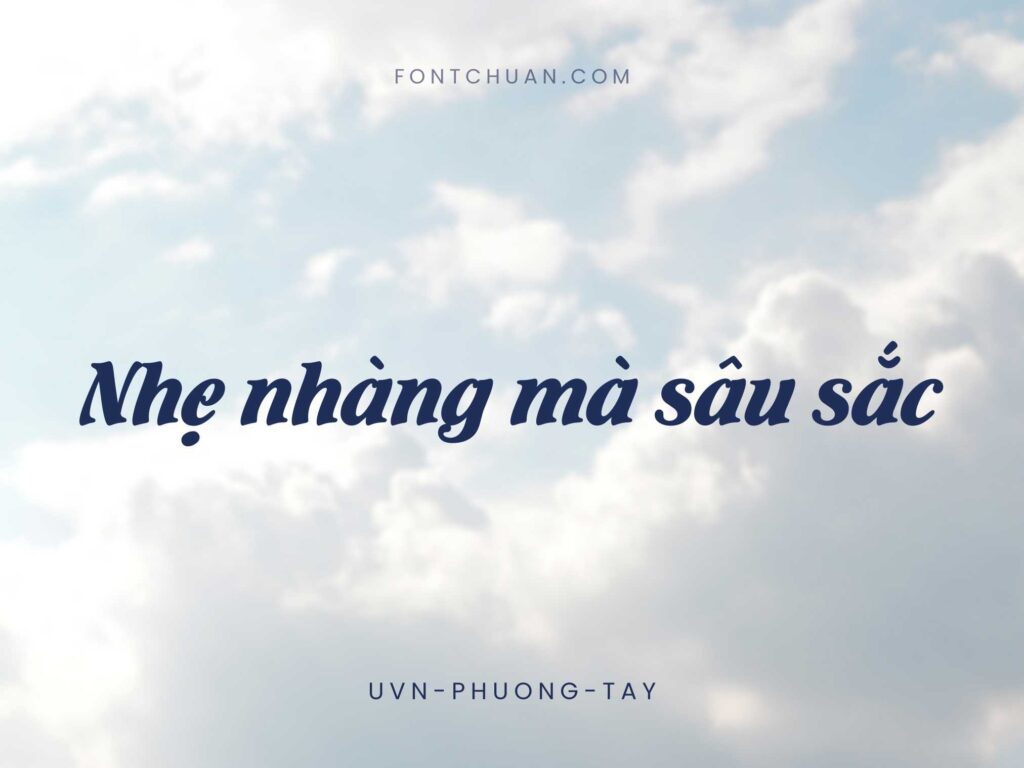
Font UVN Phuong Tay Việt Hóa
UVN Phương Tây là một phông chữ thư pháp mang phong cách nghệ thuật viết tay truyền thống. Được thiết kế với các nét bút lông mềm mại và uyển chuyển, phông chữ này tạo nên sự thanh thoát và tinh tế cho các tác phẩm thiết kế. UVN Phương Tây hỗ trợ đầy đủ các ký tự tiếng Việt, giúp người dùng dễ dàng sử dụng trong các dự án sáng tạo liên quan đến văn hóa Việt Nam.
Với thiết kế độc đáo và nghệ thuật, UVN Phương Tây phù hợp cho các ứng dụng như thiệp mời, tiêu đề sách, thiết kế logo và các ấn phẩm nghệ thuật. Trong lĩnh vực sự kiện, phông chữ này có thể được sử dụng trong các dịp như lễ hội, lễ cưới và các sự kiện văn hóa. Ngoài ra, UVN Phương Tây cũng thích hợp cho các ngành nghề như thiết kế đồ họa, nghệ thuật trang trí và xuất bản.